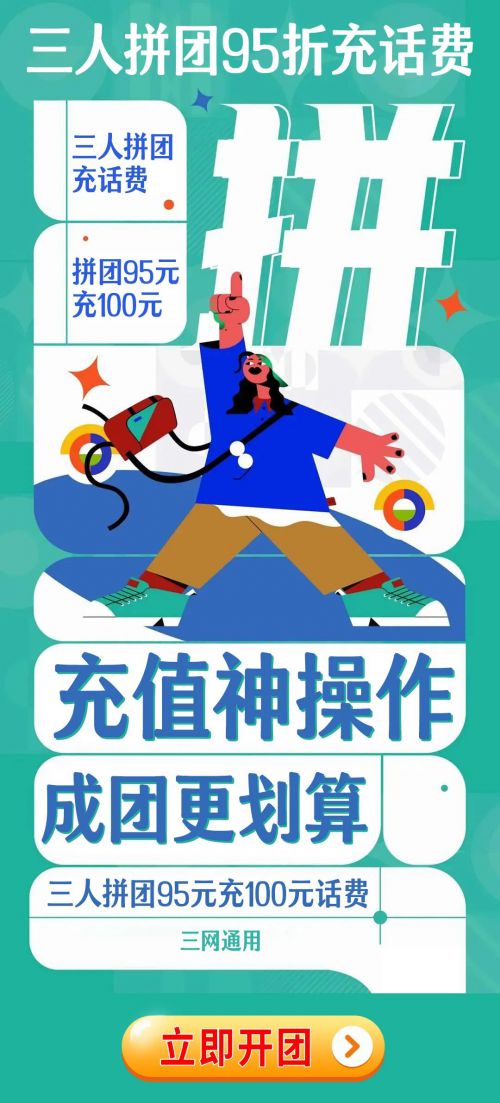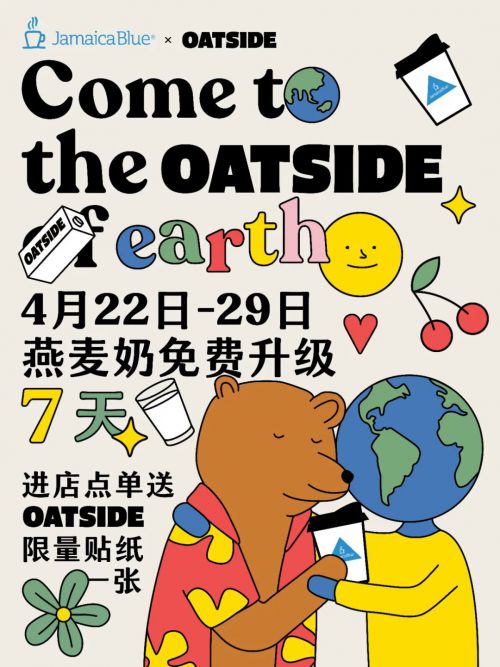
Aa汤圆体
Aa汤圆体创作时注重笔画的“美味感”,设计了带圆角的微妙的喇叭口,使其看起来柔软温润而富有弹性;Aa汤圆体横细竖粗的笔画使其错落有致,中和了圆体的甜腻感,更加清爽简约,就如同汤圆一般,内陷甜蜜多汁,外皮柔软弹牙,汤水清爽开胃。适用于儿童玩具、床上用品、食品甜品等的海报、广告等装饰性场合设计。